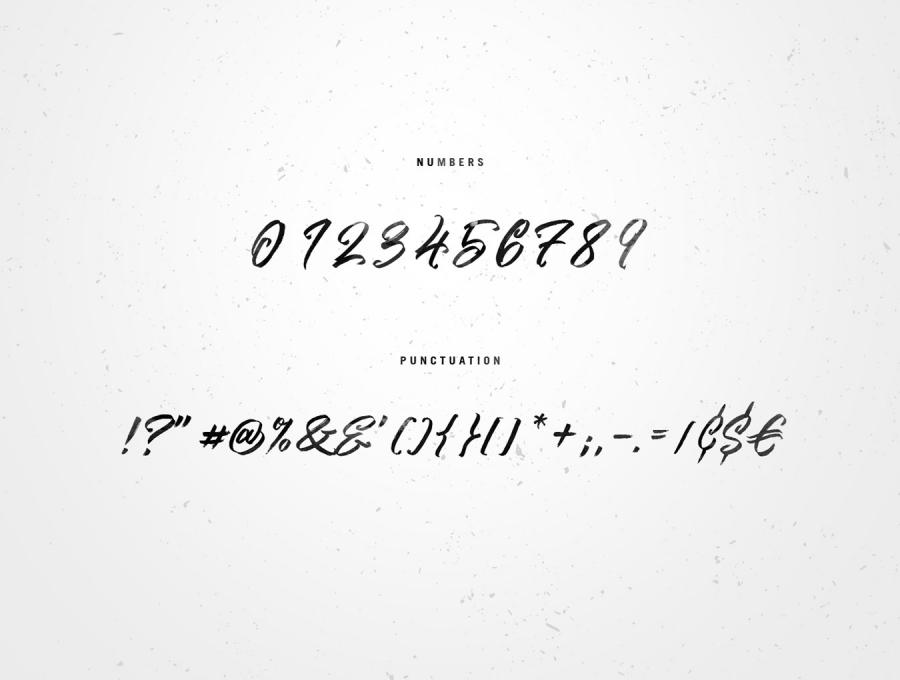
Highlander 标记 英文字体 (Highlander Marker Script)
Highlander配有一整套大小写字符,可让您将文字转换成正宗的手工刻字。 Highlander字体包含大量字形,包括数字,标点符号和多语言支持。 还包括一个额外的额外字体,其中包括扩展名,完美地补充了你的主要文本。